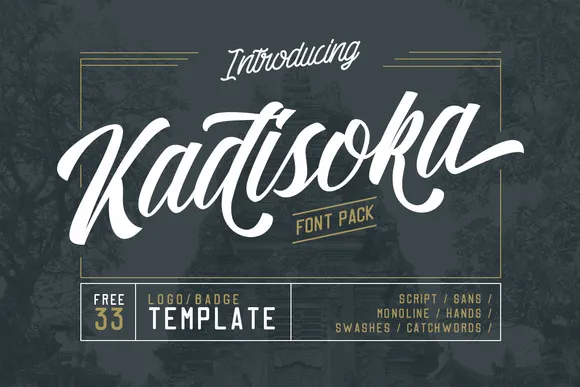
A Kadisoka Script Font é uma linda fonte brush que captura as nuances perfeitas do papel suave e das canetas artesanais. Inspirada na arte folclórica brasileira, essa elegante letra foi criada pelo designer Hamilton e traz um toque de originalidade à sua produção gráfica ou projeto personalizado. Para usuários que valorizam a profundidade e diversidade da experiência do Kaidisko Script Font, temos excelentes novidades. O arquivo full version proporciona uma gama total de 680 caracteres, além de três fontes adicionais e modelos de logotipos exclusivos. Se você é um amante dessa arte, não perca tempo: cada detalhe que você adicionar a seus projetos será mais belo graças às nuances elegantes da Kadisoka Script Font. Para quem está procurando por uma fonte única para expressar sua personalidade ou criar um design memorável, esta Kadisoka Script Font é o produto ideal. Se você opta pela versão gratuita, sabe que qualquer doação é muito apreciada e também pode se beneficiar de nossos modelos de logotipos. Com a Kadisoka Script Font em seu portfólio, está um passo mais perto de transformar suas ideias em realidade com designs únicos. Visite o link fornecido para explorar todas as possibilidades do full version e descubra como a sua produção gráfica pode ganhar uma nova dimensão.